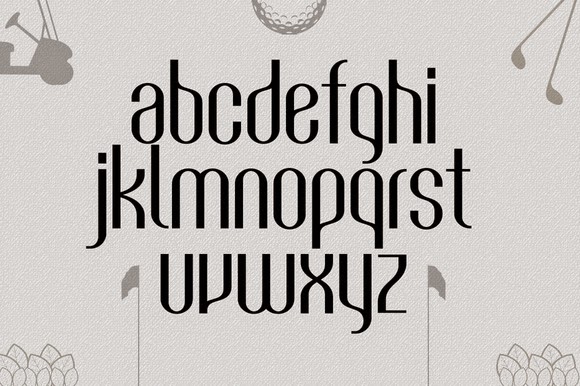
[Fashion] Golf Regular Việt hóa
Thông tin về font Golf
Golf TrueType Font is a fashionable, elegant font, suitable for advertising, design fashion, golf products, contains 227 glyphs.